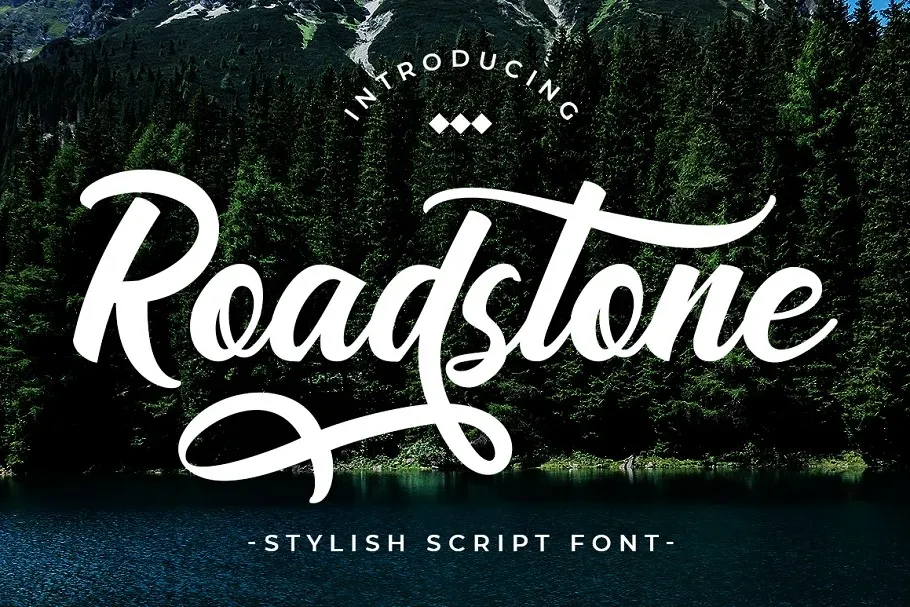
A Road Stone Font é uma elegante escolha para aqueles que procuram um estilo script moderno com influências vintage e retro. Inspirada na combinação entre estilos tradicionais americanos do passado e a arquitetura contemporânea, essa fonte oferece uma cadência suave e vibrante em cada caractere, projetada para personalizar seus projetos de moda. Seus traços rudes e robustos conferem um toque forte que assegura a estabilidade necessária para qualquer projeto gráfico, especialmente na criação de roupas ou acessórios. Além disso, a Road Stone Font tem uma beleza inegável, combinando características modernas com o charme retro. Seja você um designer gráfico ambulante criando peças únicas ou alguém que precisa encontrar fontes para seus projetos pessoais, essa fonte oferece precisão e originalidade em seu design. E como sua fonte é criada por 99designs, a qualidade de suas linhas e formas confirma um produto seguro e de alta qualidade para incorporar em seu próximo projeto gráfico.